갤럭시에 적용하는 손글씨폰트
갤럭시 스마트폰을 사용하는 분들이라면 다양한 폰트를 적용하고 분위기를 바꿀 수 있는 방법이 있습니다. 갤럭시스토어에서 원하는 폰트를 다운로드 받고 적용하면 멋지게 폰전체의 폰트를 쉽게 바꿀 수 있어요. 하지만 폰트가 너무 많고 어떤게 인기가 좋은지 내 스타일과 맞는지 확인하려면 시간이 많이 필요한데요. 이 글에서 이런 갤럭시스토어의 폰트를 쉽게 확인하고 원하는 폰트를 골라볼 수 있습니다.
귀여운 손글씨 폰트 목록
1. 널좋아해
귀여운 느낌으로 또박또박 잘 눌러쓴 글씨느낌으로 손글씨이지만 글자를 알아보기 쉬운 폰트입니다. 유료폰트로 갤럭시스토어에서 구매하여 사용가능합니다.
2. Neo달콤카라멜
손글씨느낌이 물씬 나면서도 정갈하고 작은 크기의 폰트를 보여주는 달콤카라멜폰트입니다. 유료폰트로 갤럭시스토어에서 구매하여 사용가능합니다.
3. 레몬마멀레이드
손글씨 느낌의 부드러운 곡선과 가독성이 좋은 디자인. 글자 너비가 좁아 일러스트, 웹툰, 동화책 본문에 적합합니다. 유료폰트로 갤럭시스토어에서 구매하여 사용가능합니다.
4. 볼펜쓰다
실제 볼펜으로 쓴 듯한 자연스러운 질감. 개인적이고 친근한 느낌을 줍니다. 유료폰트로 갤럭시스토어에서 구매하여 사용가능합니다.
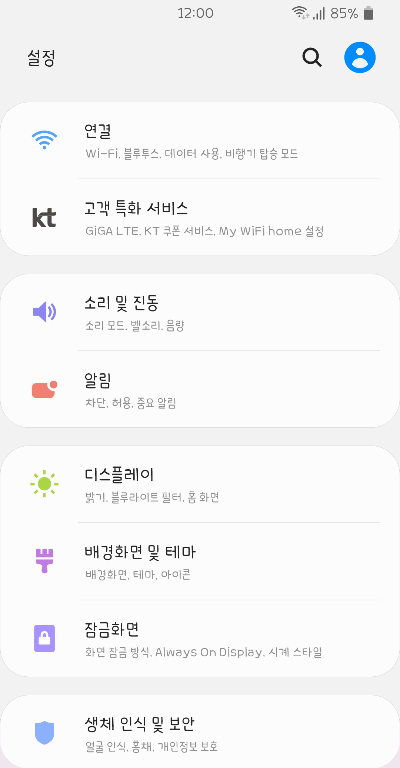
5. 얇아진뭉이뭉실
가늘고 부드러운 선이 특징. 섬세하고 여성스러운 느낌을 줍니다. 유료폰트로 갤럭시스토어에서 구매하여 사용가능합니다.
6. 이슬비오는날의수채화
수채화 느낌의 부드럽고 흐릿한 질감. 감성적이고 예술적인 분위기를 표현합니다. 유료폰트로 갤럭시스토어에서 구매하여 사용가능합니다.
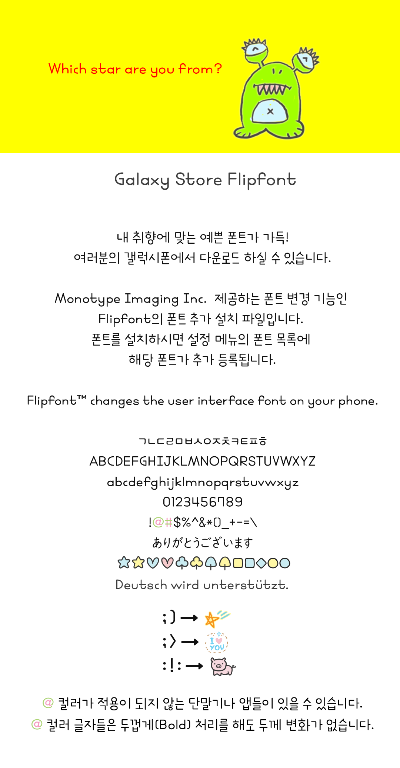
7. 어느별에서왔니
독특하고 환상적인 디자인. 우주나 판타지 관련 주제에 적합합니다. 유료폰트로 갤럭시스토어에서 구매하여 사용가능합니다.
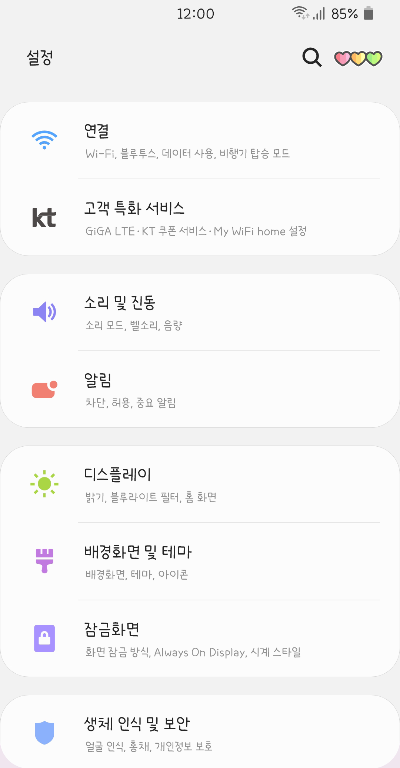
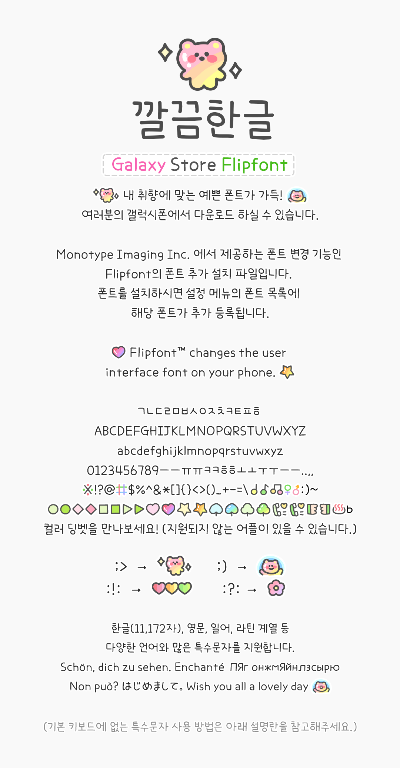
8. 깔끔한글
정돈된 선과 균형 잡힌 디자인. 가독성이 높고 공식적인 문서에 적합합니다. 유료폰트로 갤럭시스토어에서 구매하여 사용가능합니다.
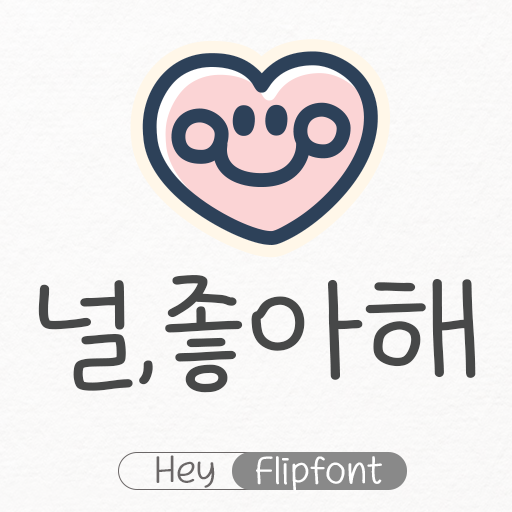
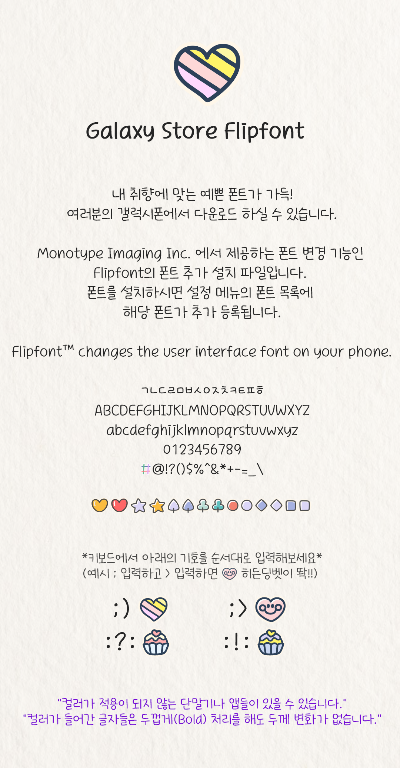
9. 널좋아해
귀엽고 친근한 손글씨체. 사랑스럽고 감성적인 메시지 전달에 적합합니다. 유료폰트로 갤럭시스토어에서 구매하여 사용가능합니다.
10. 럭키몽이잖아
재미있고 활기찬 디자인. 유쾌하고 긍정적인 분위기를 연출합니다. 유료폰트로 갤럭시스토어에서 구매하여 사용가능합니다.